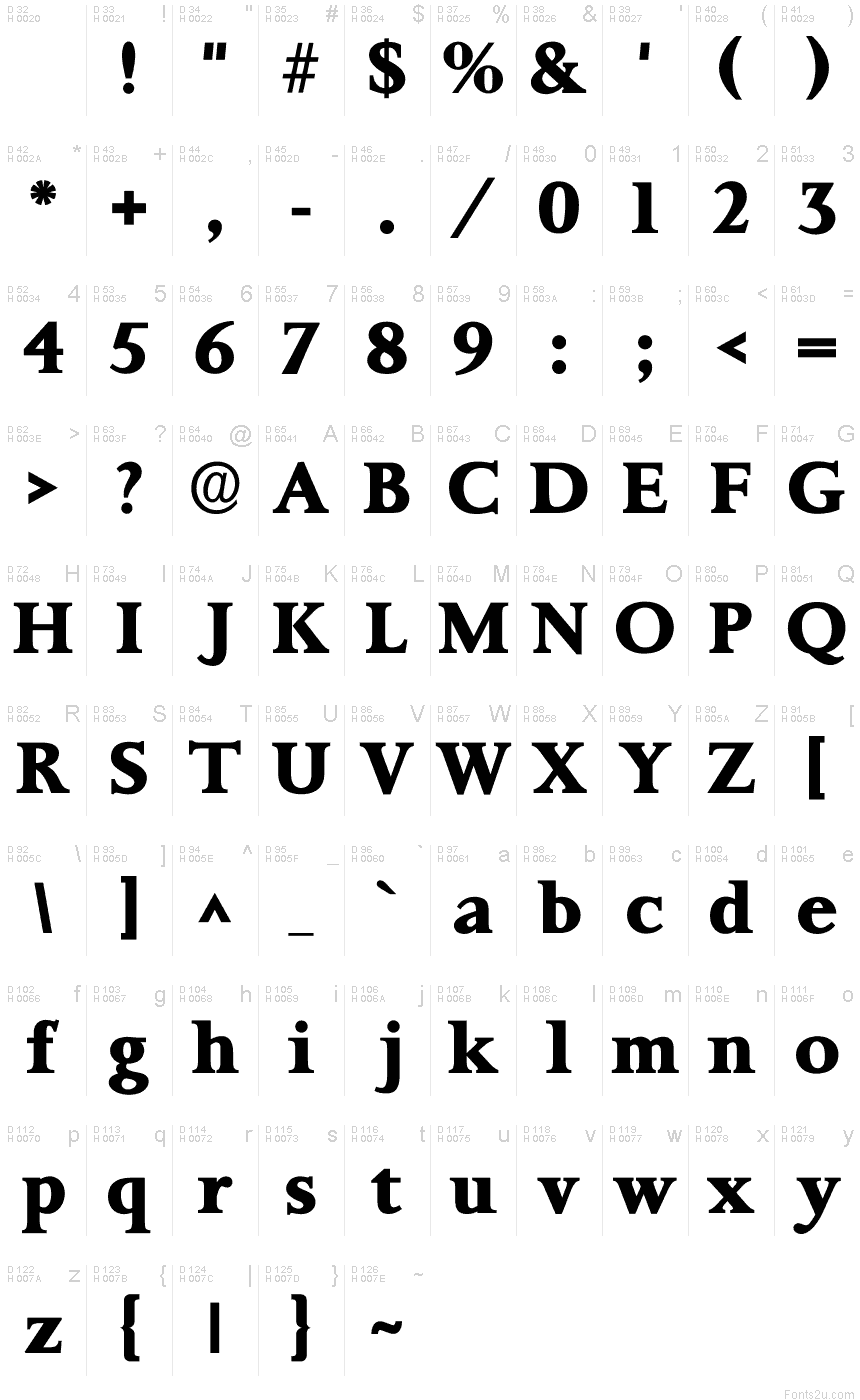
Palermo Bold od B and P Graphics je bezplatné patkové písmo definované širokou, těžkou siluetou a hlubokými přečnívajícími patkami, které dávají písmenům vzhled tesaného nápisu. Opakující se zaoblené spoje a výrazný horizontální důraz dodávají designu váhu a dramatičnost, namísto knižní strohosti.
Tato hmota se skvěle hodí pro branding restaurací, vinné etikety, plakátové titulky, obaly a výlohy, kde klasické patkové písmo potřebuje spíše prezentovat než se držet zpátky. Krátké titulky a názvy těží nejvíce, zejména v layoutu, který dokáže využít tyto vyčnívající kapitálky a kompaktní oblouky jako součást vizuálního rytmu.